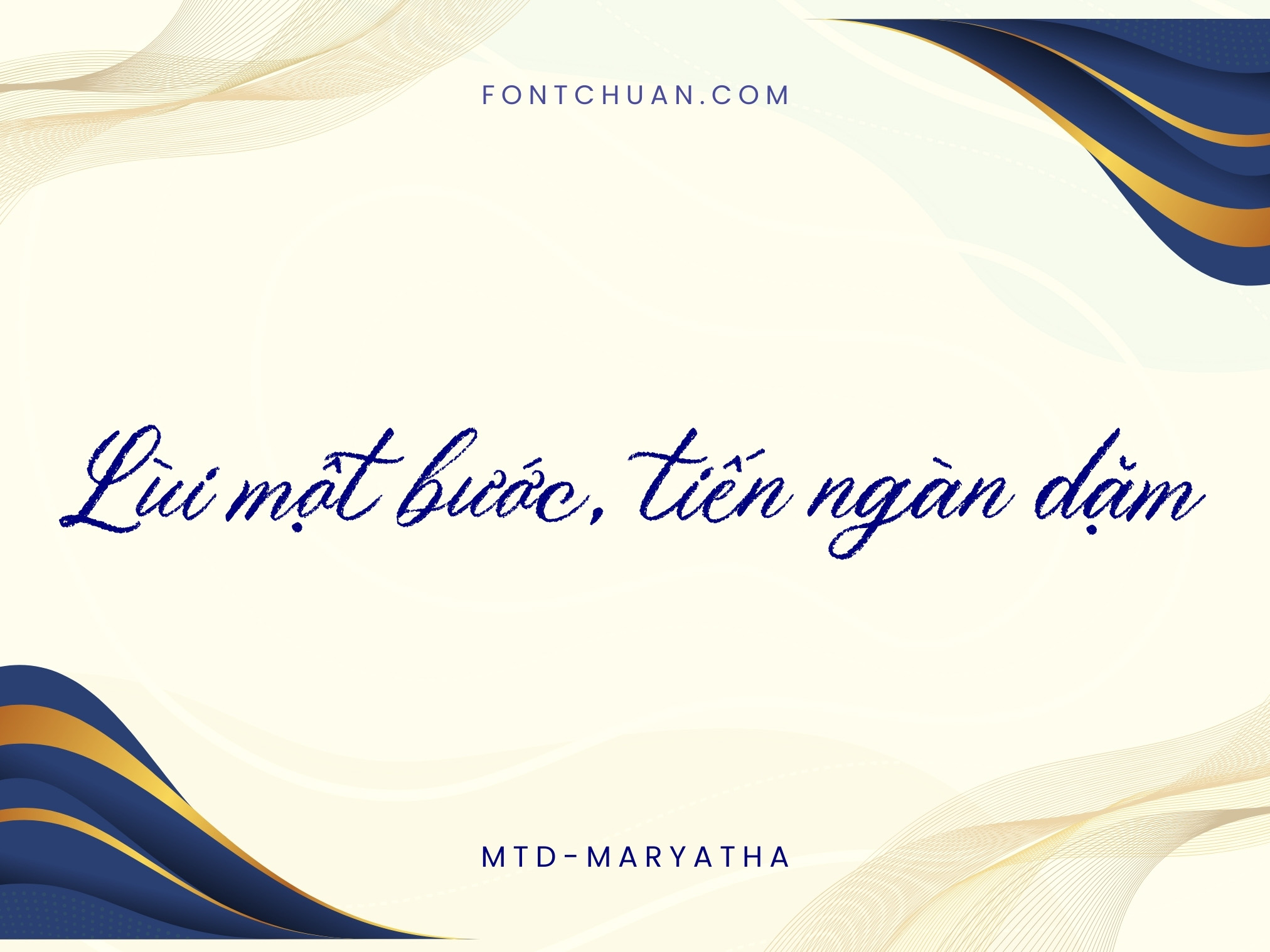
Font MTD Mtd Maryatha Việt Hóa
Tác giả Font: Ryan Prasetya
Font MTD Maryatha là một phông chữ viết tay với kết cấu bút sáp độc đáo, tạo cảm giác như chữ viết tay tự nhiên. Được thiết kế bởi Ryan Prasetya và Việt hóa bởi Mộc Hạ, font này hỗ trợ đầy đủ tiếng Việt và hơn 90 ngôn ngữ khác, mở rộng khả năng ứng dụng trong các thiết kế đa ngôn ngữ. Đây là một trong những phông chữ được cộng đồng thiết kế đánh giá cao và sử dụng trong nhiều dự án sáng tạo, đáp ứng nhu cầu đa dạng của người dùng.
MTD Maryatha nổi bật với phong cách viết tay tự nhiên và kết cấu bút sáp độc đáo, mang đến cảm giác thân thiện và gần gũi. Font rất phù hợp cho các thiết kế logo, tiêu đề, bao bì sản phẩm, thiệp mời và các ấn phẩm đòi hỏi sự sáng tạo và cá nhân hóa. Các ngành nghề phù hợp bao gồm quảng cáo, giáo dục, công nghệ, thiệp cưới và ảnh cưới. Font này cũng lý tưởng cho các sự kiện như Tết, Giáng sinh, Valentine và các lễ hội khác.